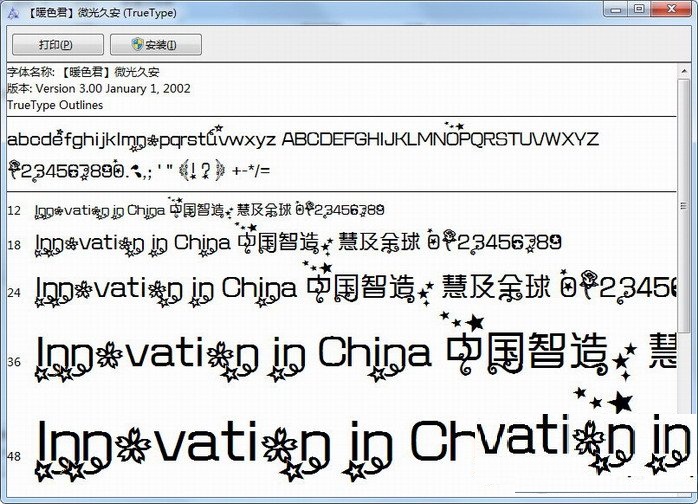
微光久安字體是一款專門為用戶設(shè)計(jì)的中英文字體,實(shí)用與網(wǎng)絡(luò)聊天、藝術(shù)廣告等行業(yè),字體打出了十分好看,現(xiàn)小編為所需用戶提供微光久安字體下載,歡迎體驗(yàn)!
包含了各種炫麗閃亮的圖案符號(hào),字體打出來也十分的好看
主要適用于網(wǎng)絡(luò)文字聊天、藝術(shù)廣告、書籍印刷等方便